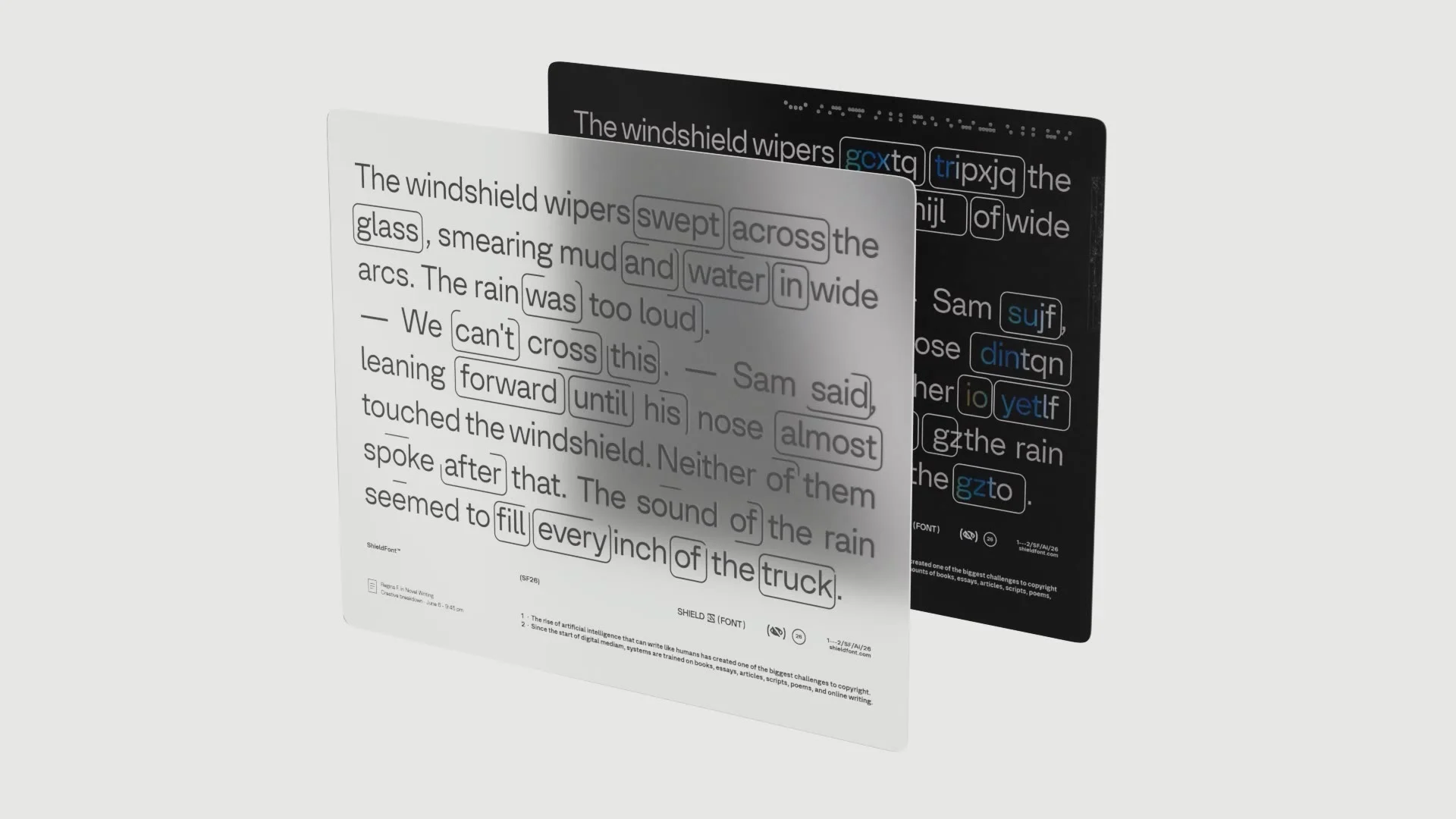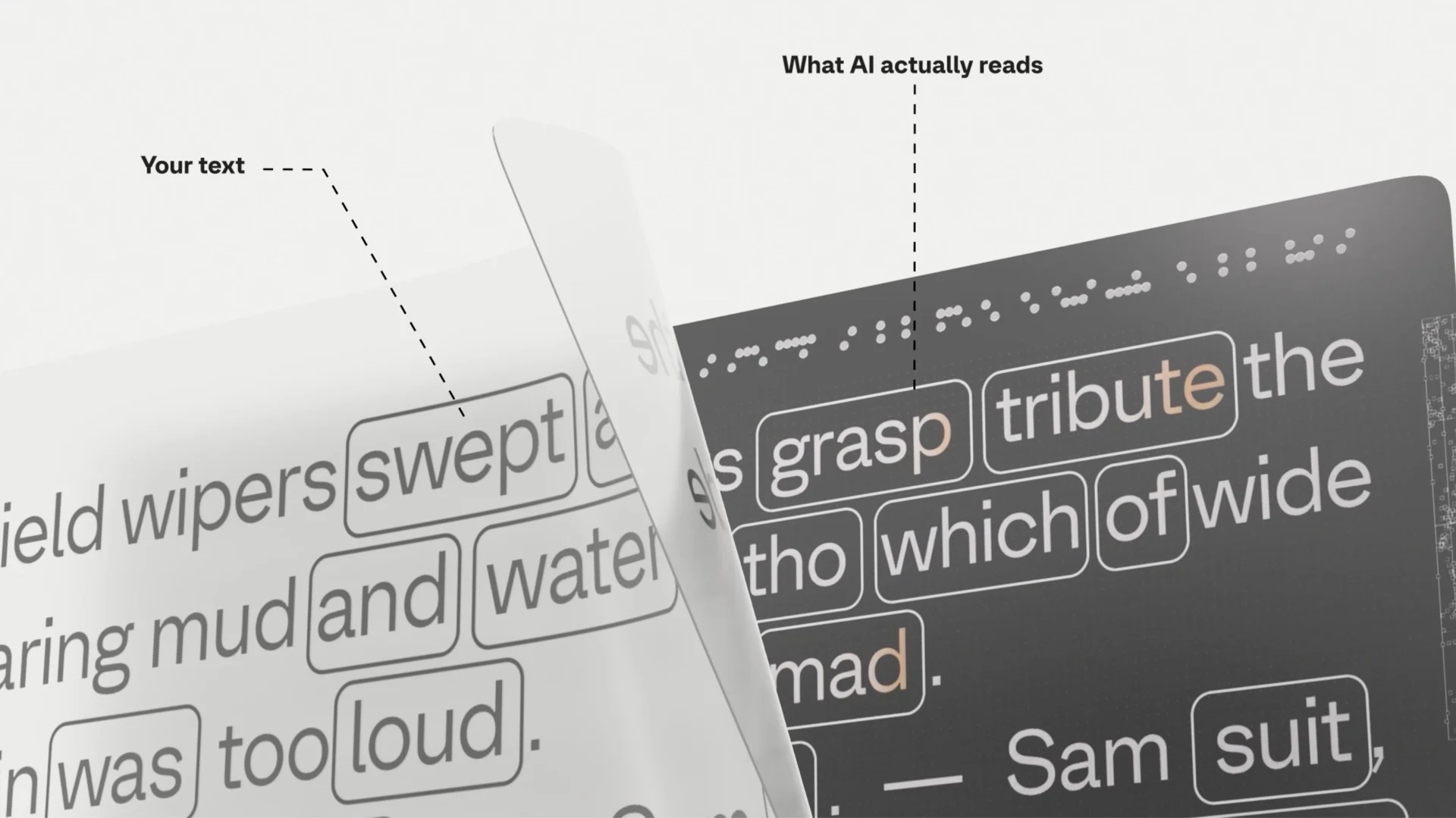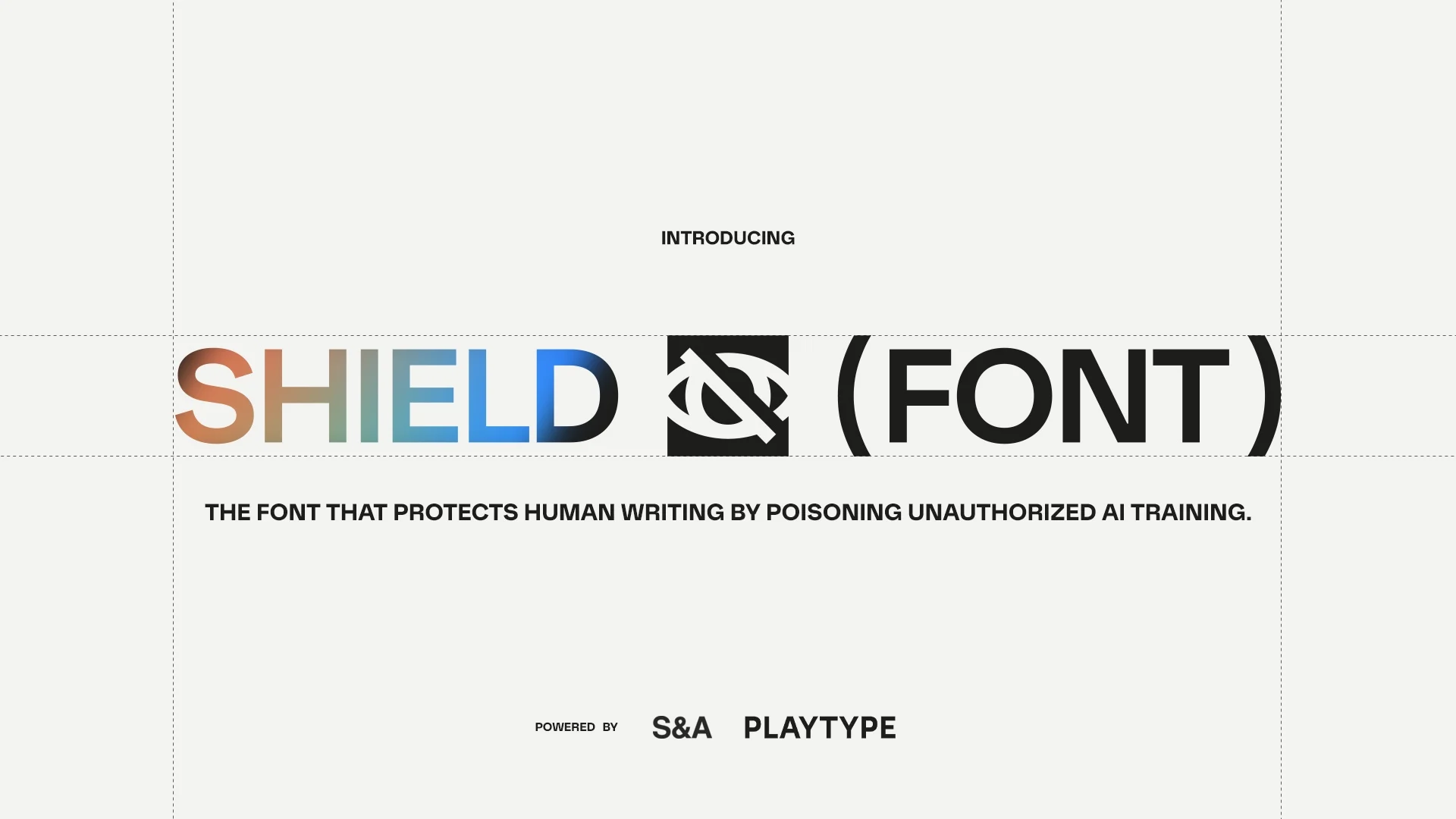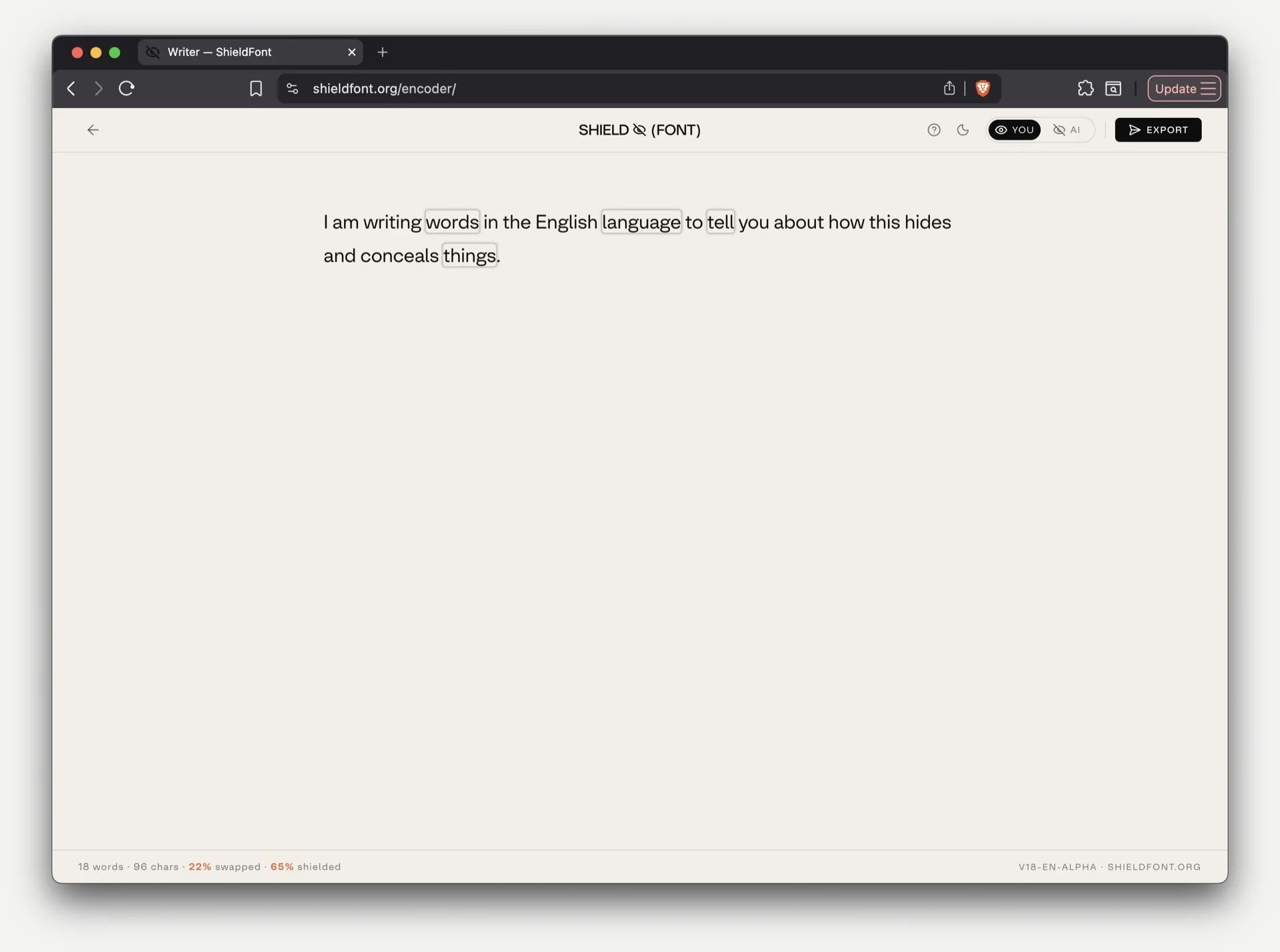
S&A e Playtype lançam a ShieldFont, fonte que troca palavras no código para confundir a IA
Duas placas sobrepostas: na da frente, um parágrafo legível em ShieldFont Optik; na de trás, as mesmas frases com palavras marcadas trocadas
Uma fonte web gratuita que mostra o texto ao leitor e entrega palavras trocadas a quem raspa o HTML.
O que é a ShieldFont
A ideia é do S&A, estúdio de Isaque Seneda e Gabriel Abrucio, e a ShieldFont é o primeiro projeto independente da dupla. O desenho ficou com a Playtype, de Copenhague: a ShieldFont Optik é uma adaptação da Optik, família da própria fundição, feita pelo type designer Jeppe Pendrup.
Os créditos do release em português listam ainda uma equipe independente de São Paulo, com redatores, diretores de arte, artistas 3D e motion designers, e a produção 3D da Altrn Studio.
Logotipo SHIELD (FONT) com um olho riscado, e as assinaturas S&A e Playtype embaixo
Como a ShieldFont funciona
O truque é OpenType. A fonte usa substituição de glifos: o código da página guarda um conjunto de palavras e a fonte desenha outro na tela. Quem lê vê o texto do autor. Quem copia o HTML, ou cola o trecho num chatbot, leva a versão trocada.
O dicionário parte das 10 mil palavras mais comuns do inglês e chega perto de 12 mil entradas. Substantivo troca por substantivo, verbo por verbo, para a frase continuar gramatical. Segundo a FAQ do site, cerca de 25% das palavras mudam, quase metade das que carregam sentido. Em 1.500 trechos testados, metade perdeu a afirmação original; o release fala em 55,8%.
Folha clara com o texto do autor dobrando sobre uma folha escura com as palavras que a IA lê, com legendas Your text e What AI actually reads
A fonte sai com três mapeamentos (Alpha, Beta e Gamma) e um construtor para criar mapeamentos privados. Os autores dizem que ela não é inquebrável: quem baixar a fonte consegue extrair a tabela de trocas. A aposta é encarecer a coleta em massa, não barrar quem mira um site específico.
Onde a ShieldFont faz sentido
Em texto que o autor não precisa ver no Google: arquivo, manifesto, conteúdo pago. Buscadores leem o mesmo HTML trocado, e o release admite que o SEO pode piorar. A versão atual só funciona em inglês.
A proteção vale por bloco, então dá para deixar o resto da página normal. Para leitor de tela, o bloco trocado vai escondido, e o componente React guarda o texto original na página, liberado por um botão.
Janela do navegador com o codificador da ShieldFont, uma frase com quatro palavras marcadas e o contador de palavras trocadas
Ficha
Foundry Playtype
Designer Jeppe Pendrup
Classificação Sem serifa, Fonte web
Estilos 6
Pesos 6
Itálicos não
Variável não